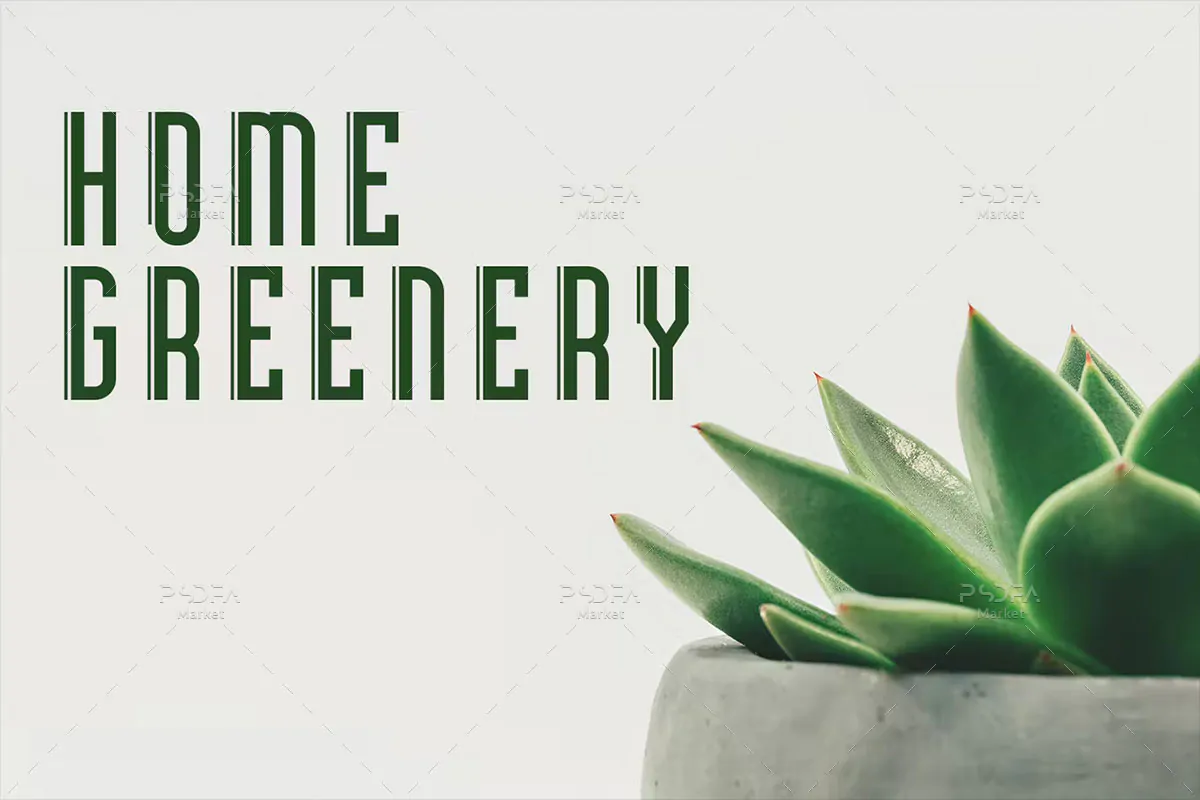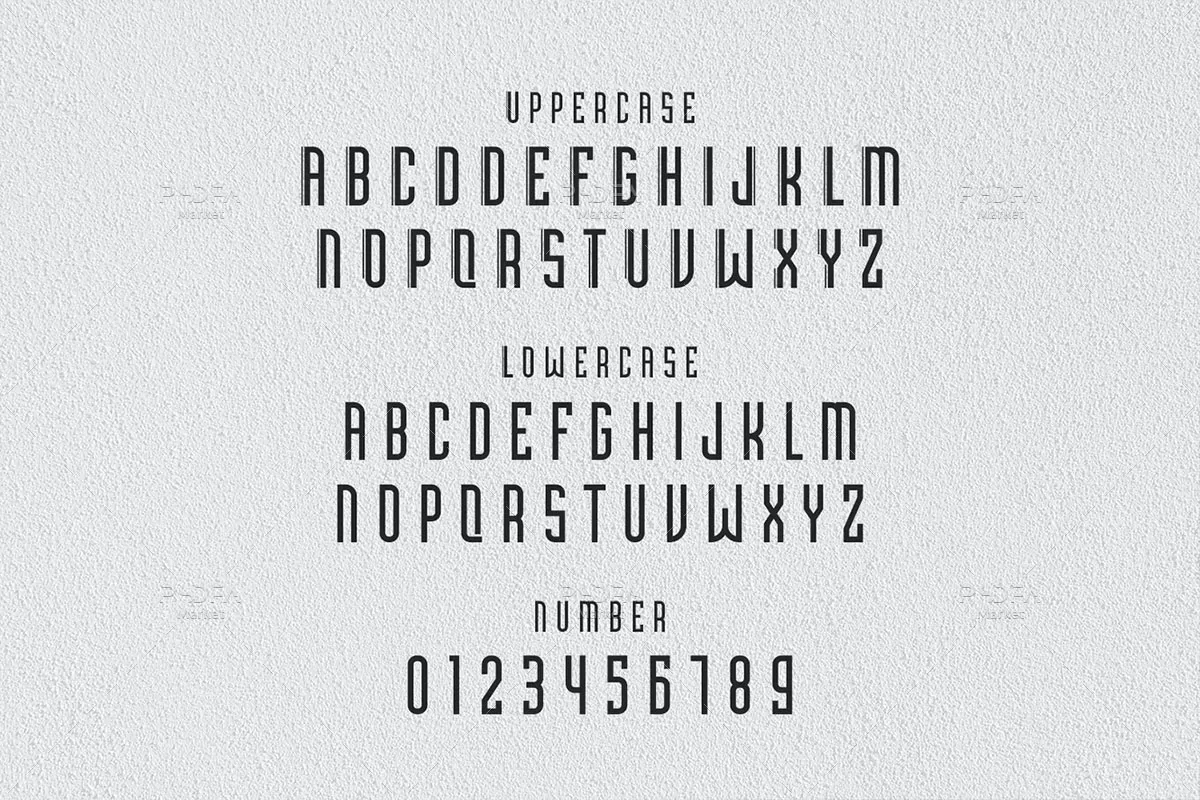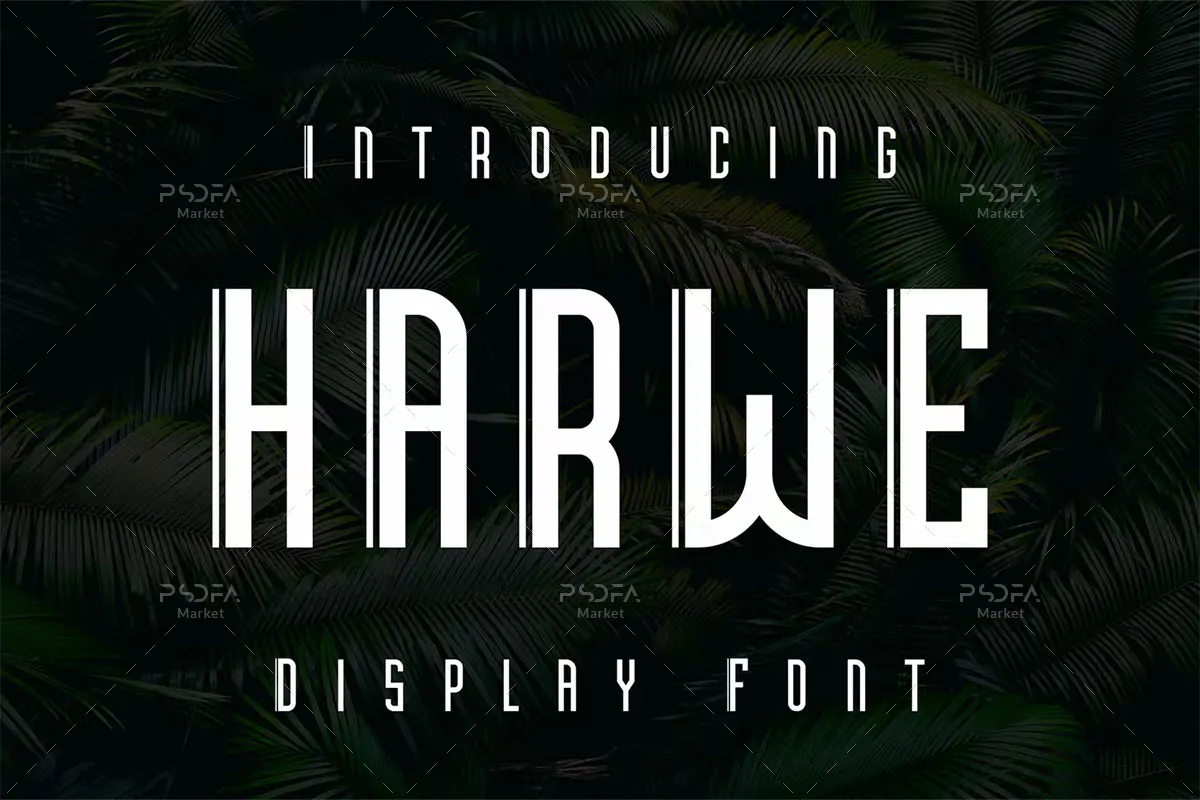
فونت طراحی لوگو Harwe
فونت طراحی لوگو
فونت طراحی لوگو Harwe یک قلم سنس سریف انگلیسی زیبا است که مناسب جهت استفاده در طرح و پروژههای گرافیکی مختلف میباشد. این فونت زیبا با وزن معمولی طراحی شده است که میتوانید از آن در طراحی لوگو، پوستر، کارت ویزیت، بروشور، تراکت، بسته بندی محصولات و … استفاده کنید.